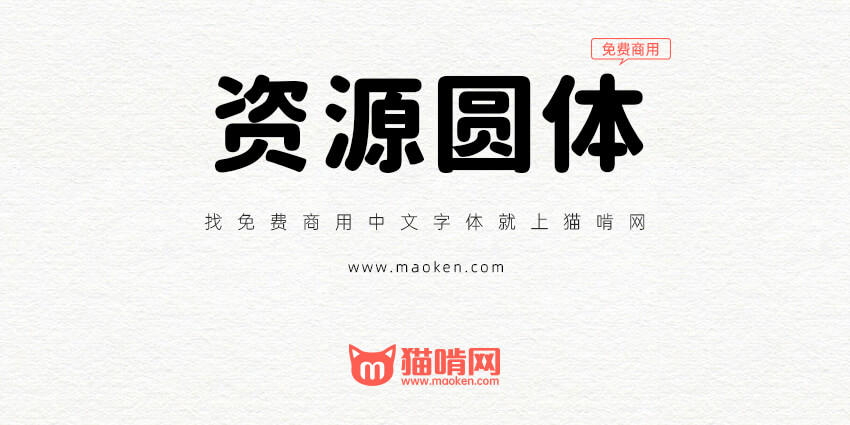
资源圆体:基于思源黑体的圆体字型 换掉思源柔黑体吧
字体作者:Cyano Hao (中国大陆) 字体字重:7个
说起可以免费商用的圆体字型,大家可能都会想到源柔黑体(国内网站上都叫“思源柔黑”), 对于国内的设计师们来说,猫啃网并不推荐使用源柔黑体。 本站已经在《源柔黑体:日本自家製フォント工房改造的思源字体》这篇文章上介绍过源柔黑体的缺点了,大家有兴趣的话可以再看一下。
对于替换掉源柔黑体的字体,猫啃网之前推荐过台湾版的源泉圆体 ,现在继续推荐另外一款字体资源圆体。资源圆体是圆内设计师Cyano Hao基于中国版的思源黑体改造而成的圆体字体。
资源圆体是思源黑体的直接变圆版,所以它的特徵跟源柔黑体基本上是一样的,但是资源圆体对简体支持十分好!简体不缺字!而且资源黑体和思源黑体一样,拥有7个字重(优秀),基本上满足大部分的设计需求。所以猫啃网推荐使用这款字体替换掉你电脑上的源柔黑体吧。
与源泉圆体有何不同?
资源圆体与源泉圆体最大的区别就是字体的笔画上有所不同。资源圆体保留着字体的脚,而源泉圆体把字体上的脚都拔除了。